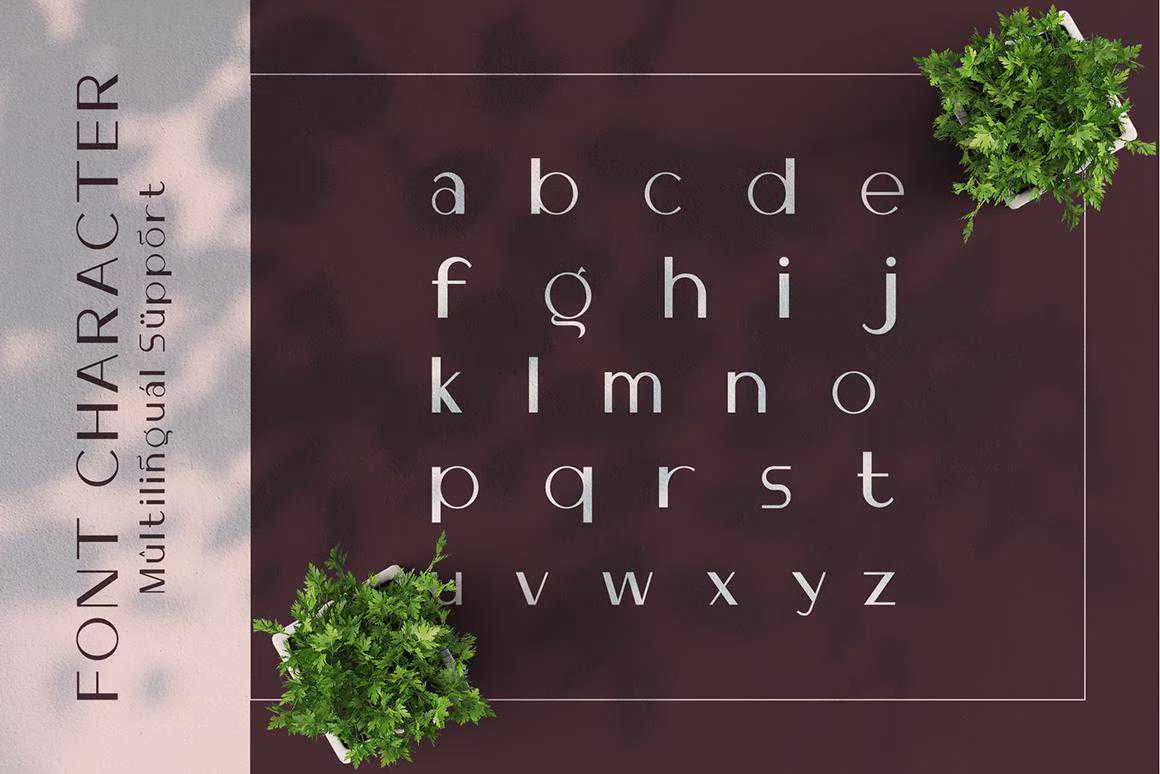
VallènSans是一款极简且独特的标准字体。这款伟大的字体在传统设计和当代设计中都体现了安全的eLingofRefinement。这款字体可使字体和徽标具有流畅的外观和风格。专为大字体显示设置而设计。它适用于标题、标题、海报、杂志、徽标、广告、邀请函、花押字、,无论你的创意是什么,VallènSans都是一款极简的、令人印象深刻的、系列化的字体。这款伟大的字体在传统和当代设计中都呈现出安全的高清晰效果。这款字体可以使字体和徽标具有独特的风格和外观。专为大字体显示设置而设计。它适合标题、标题、海报、杂志、徽标、广告、,邀请函,花押字,以及你创作的目的地。